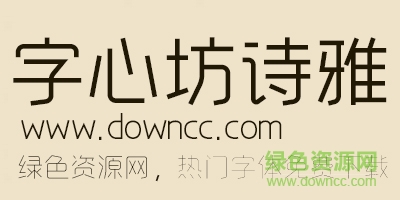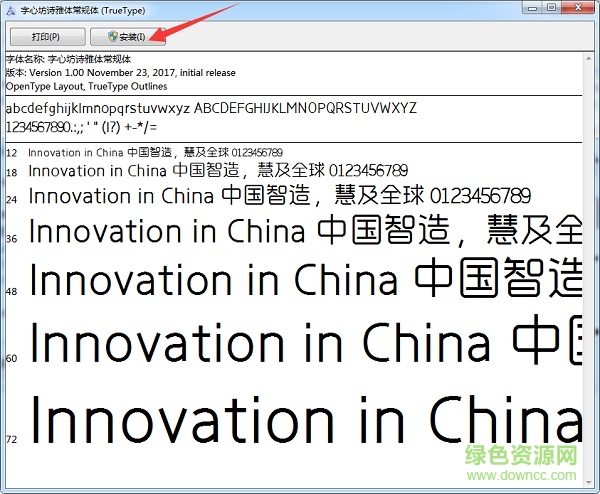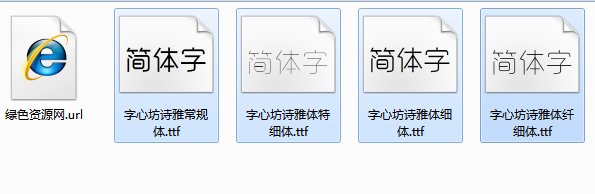
從上到下依次為字心坊詩雅常規(guī)/細/纖細/特細字體。
字體風格簡約/古風/時尚/無襯線
推薦場景:標志/導(dǎo)視/書籍/游戲/動漫
字體采用非襯線設(shè)計,全部筆畫采用直線設(shè)計。字體個性鮮明,字形特點時尚新穎,同時融入古風結(jié)構(gòu),靈活多變的線條造就此款字體的與眾不同。字體風格新穎、時尚。